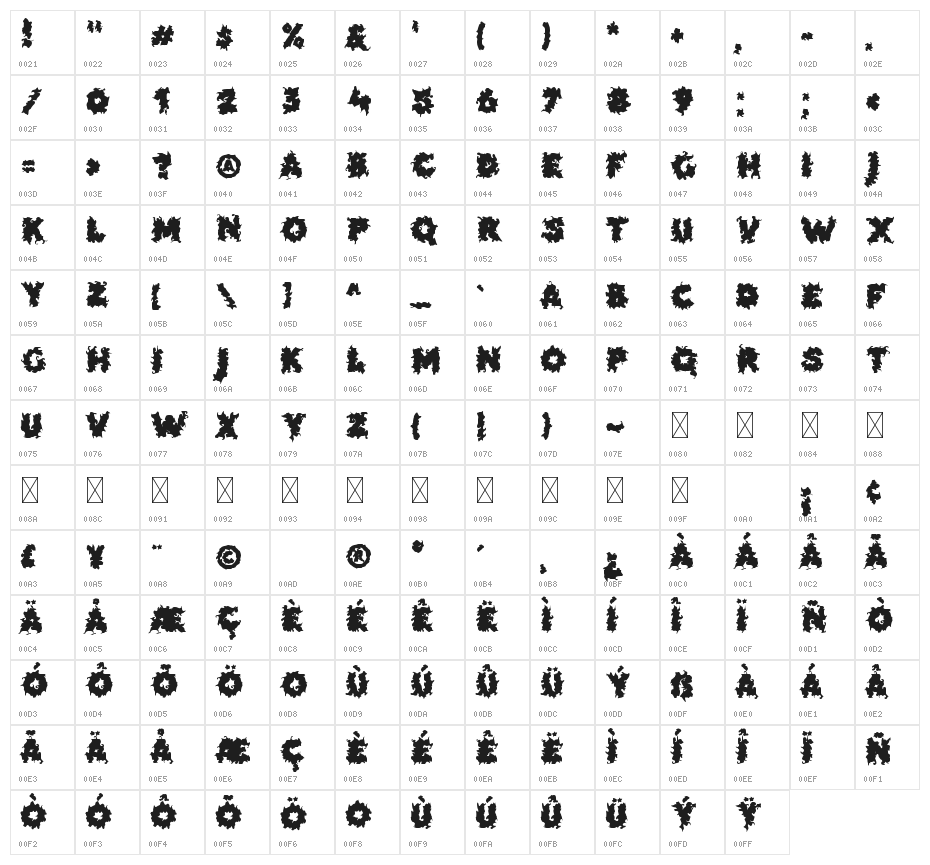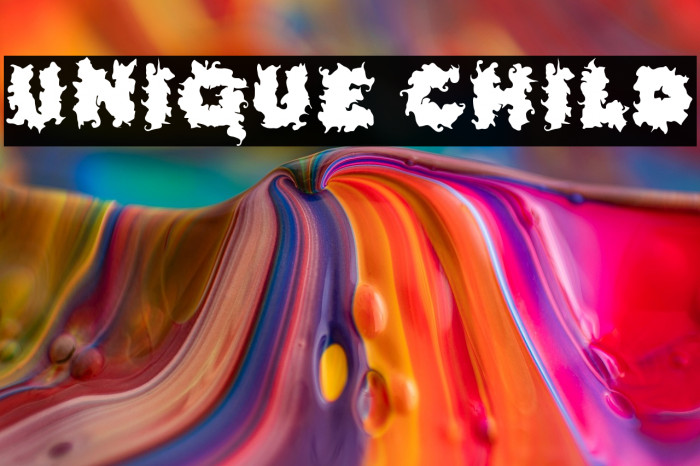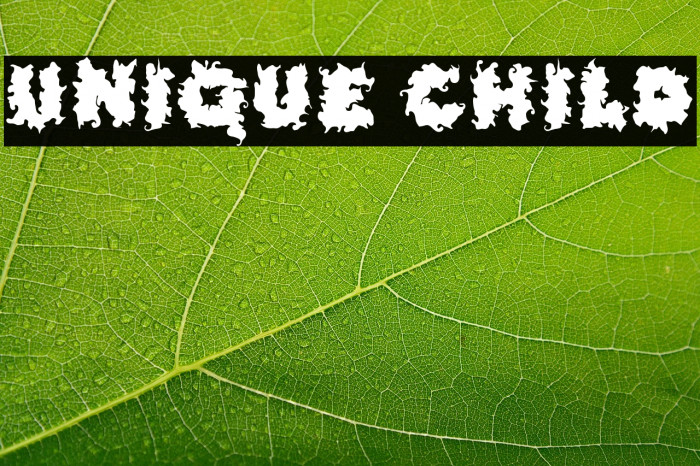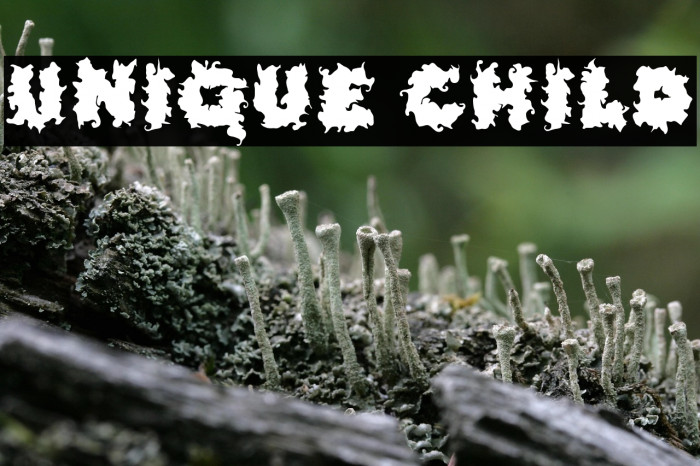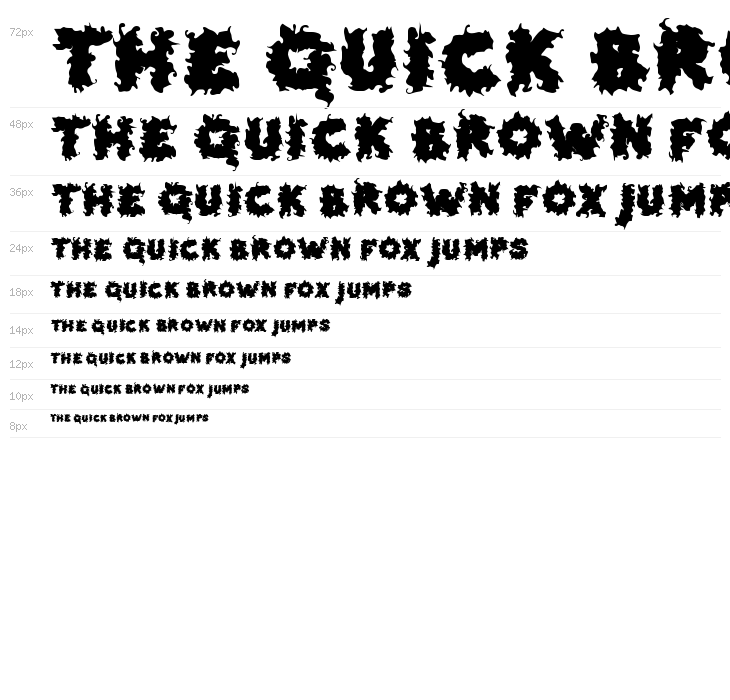
Unique Child Font
| 推荐项目 | Ideal for Halloween-themed designs, edgy posters, album covers, or any project needing a dramatic and intense visual impact. |